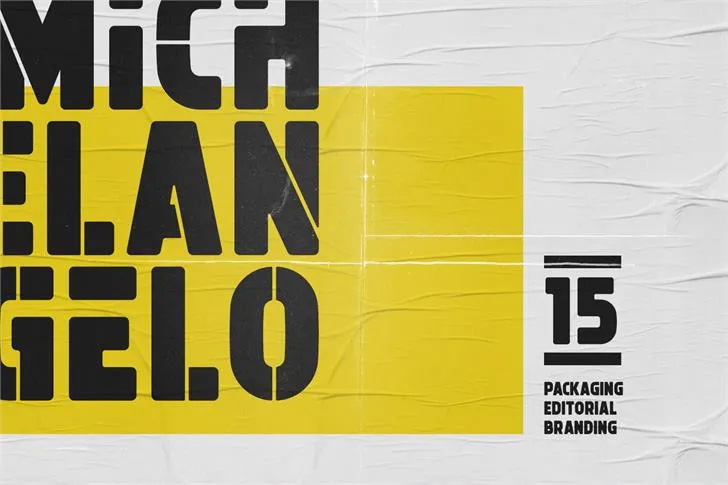
Michelangelo Font Demo – Fonte Grátis
Michelangelo Font Demo
Estamos felizes com a sua curiosidade pelo Michelangelo Typeface Family. Este é um tipo de exibição forte e único, projetado para desafiar suas limitações criativas ao criar designs de camisetas inovadores. Com seu design robusto do tipo sans-serif e influências vintage modernas, Michelangelo oferece uma variedade extensa de 15 estilos, cada um com linhas atraentes e fortes. Este tipo é perfeitamente adaptado para uso em gráficos, sinais comerciais, design editorial ou qualquer aplicação de exibição. O Designer Hamilton criou este tipo abrangente, pensando nos recursos opentype poderosos, incluindo suporte para várias línguas e moedas, tornando-o perfeitamente adaptável para a web também. Experimente o Michelangelo e veja como ele pode transformar suas criações de design.